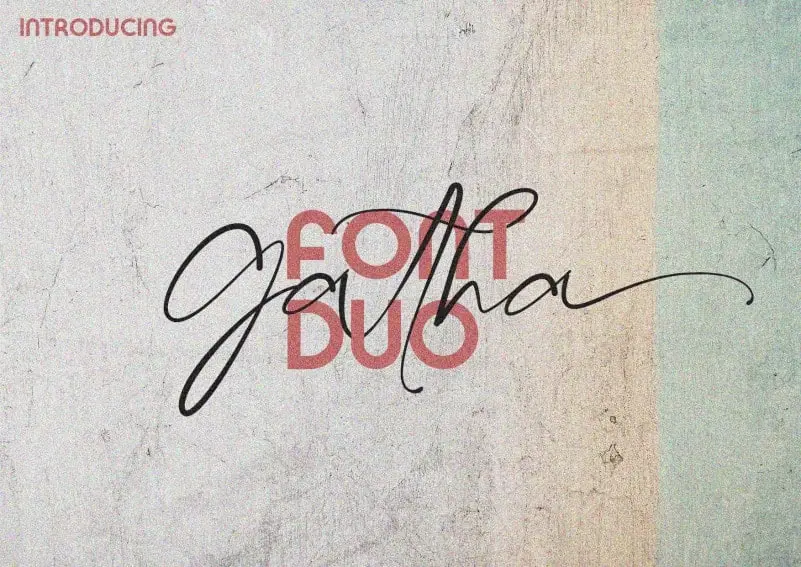
Free Gatha Font Duo – Fonte Grátis
Free Gatha Font Duo
A Gatha Font Duo é uma dupla de fontes românticas que inclui um estilo script icônico e uma fonte séria elegante, já combinados e prontos para usar juntos na sua próxima criação! Esta fonte original do designer khaiuns é ideal para quem busca personalidade em seu design sem abandonar a simplicidade e o equilíbrio de um tipo geométrico. Perfeita tanto para criar textos agradáveis quanto para dar um toque distintivo às suas imagens, essa dupla de fontes vem pronta para ser usada juntas, tornando-a uma excelente opção para os criativos que buscam uma mistura interessante e harmoniosa entre a elegância moderna e o charme tradicional do texto. Aproveite este design inovador para dar vida a seus projetos de design gráfico, seja em cartazes, logotipos ou até mesmo em aplicativos digitais. Descubra agora o poder da Gatha Font Duo!